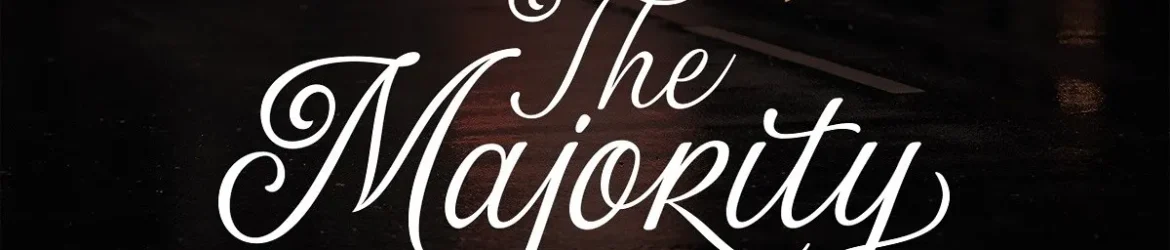
A The Majority Font é uma fonte script que oferece um toque refinado e elegante aos projetos digitais. Ela se destaca por sua beleza clássica, fluidez perfeita e capacidade de criar ambientes luxuosos em design, seja para camisetas, logotipos ou letras criativas. Este script é extremamente versátil e pode ser aplicado a diversos usos como headlines, assinaturas, citações e letras de quizes. É uma fonte perfeita tanto para designers profissionais quanto para iniciantes que desejam adicionar um toque sofisticado ao seu trabalho. A The Majority Font vem completa com códigos maiúsculas e minúsculas, pontuação, símbolos e números, além de alternativas estilizadas, ligações, e muitos outros recursos para criar a melhor experiência possível no seu design. Esperamos que você goste da The Majority Font e encontre essa fonte como uma extensão perfeita para sua paleta de ferramentas digitais.